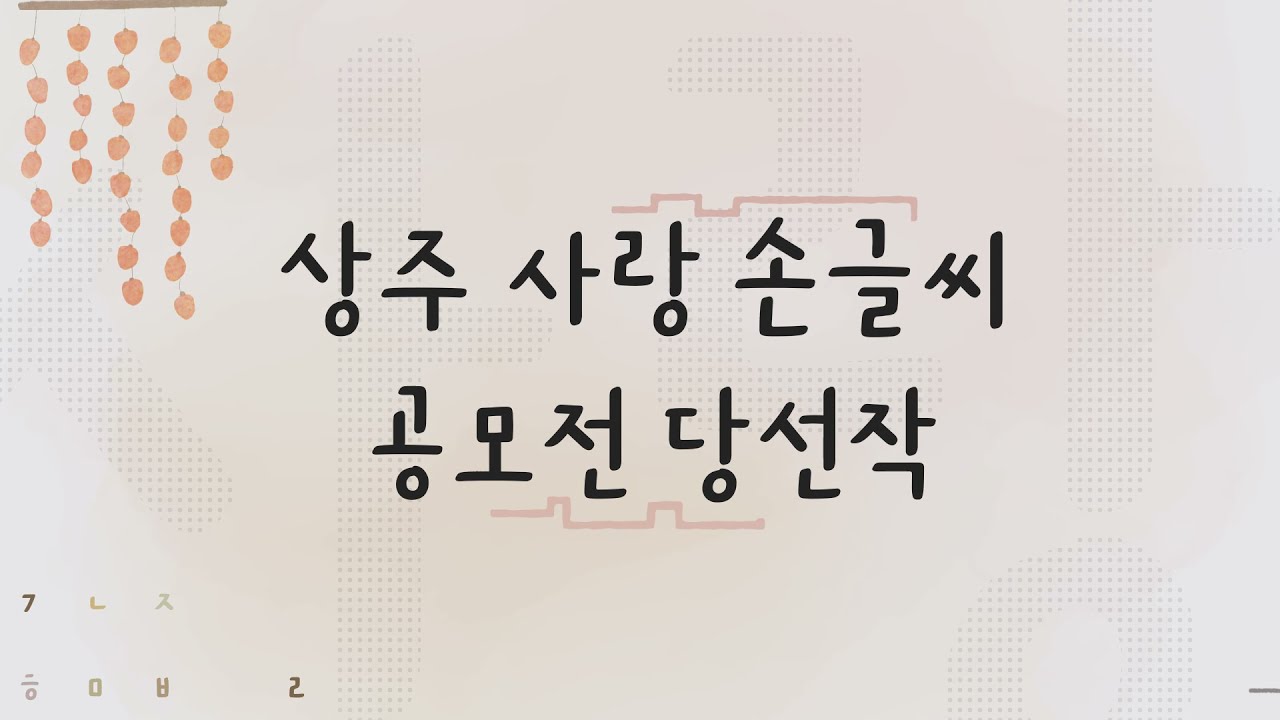
상주다정다감체
상주에서 주최된 '상주 사랑 손글씨 공모전' 당선작으로 개발된 서체입니다. 손글씨의 리듬감이 느껴지도록 디자인되었습니다.
상주다정다감체
상주에서 주최된 '상주 사랑 손글씨 공모전' 당선작으로 개발된 서체입니다. 손글씨의 리듬감이 느껴지도록 디자인되었습니다.
상주시에서 주최된 '상주 사랑 손글씨 공모전' 당선작으로
개발된 서체입니다. 손글씨의 리듬감이 느껴지는 서체입니다.